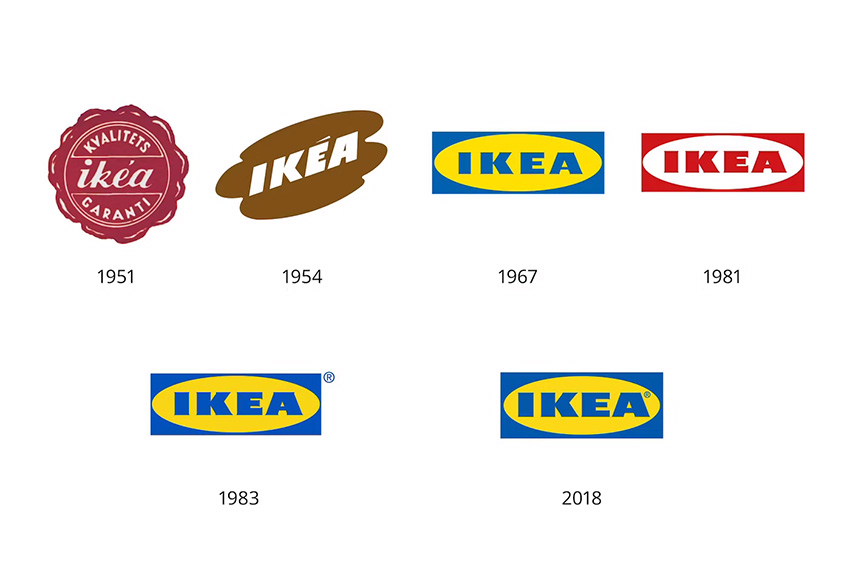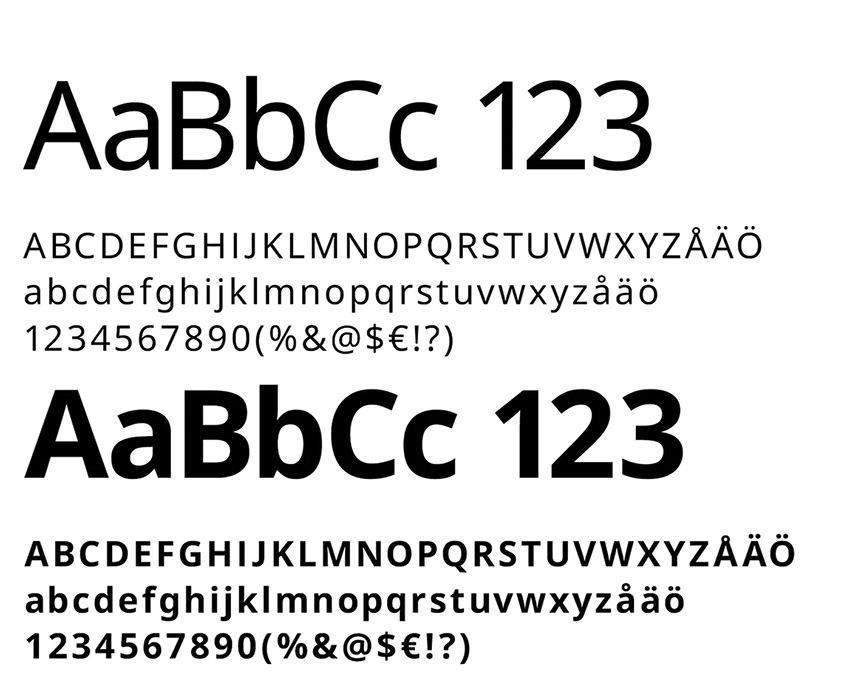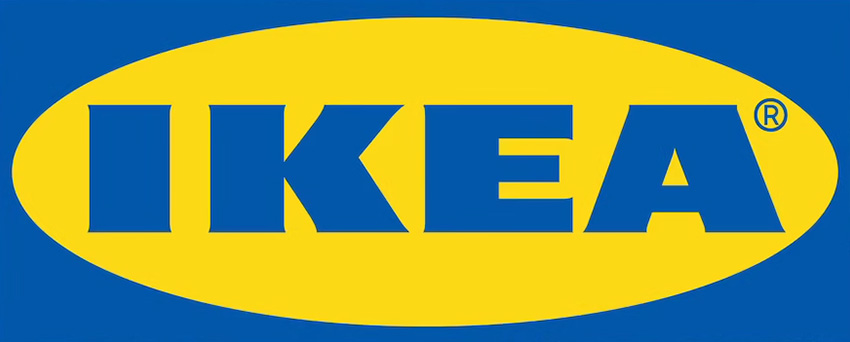
What Font Does IKEA Use?
IKEA ist weltweit bekannt für seine gut gestalteten, kostengünstigen Möbel und Haushaltswaren, und das blaue und gelbe IKEA-Logo ist ebenfalls zu einem Symbol geworden. Erfahren Sie alles über die IKEA-Logo-Geschichte, Farben, Schriftart und mehr.
IKEA-Logo. Quelle: IKEA-Website
Welche Schriftart verwendet IKEA?
Lassen Sie uns damit beginnen, die Frage zu beantworten: „Welche Schriftart verwendet IKEA?“
Die Schriftart des IKEA-Logos basiert auf einer benutzerdefinierten Schriftart namens IKEA Sans, die von Robin Nicholas entworfen wurde.
Laut der IKEA-Website basiert die Schriftart des IKEA-Logos auf einer Extrabold-Version der Futura-Schriftart, bei der kleine Serifen zu den Buchstaben hinzugefügt wurden, um die Klarheit und Lesbarkeit zu verbessern.
IKEA Sans-Schriftart
Die IKEA Sans-Schriftart. Quelle: IKEA-Website
IKEA-Logo-Geschichte
Wussten Sie, dass das Original-IKEA-Logo von 1951 rot war, weil der Gründer, Ingvar Kamprad, dachte, dass die Farbe niedrige Preise symbolisierte?
Noch mehr IKEA-Kuriositäten für Sie: Der Name basiert auf den Initialen des Gründers, gefolgt von den Initialen des Bauernhofs und der Gemeinde, in der er aufgewachsen ist. Und auf Schwedisch wird es „ee-kay-uh“ ausgesprochen, nicht „eye-kee-uh“.
Abgesehen von einem Flirt mit Braun im Jahr 1954 und einer kurzzeitigen Rückkehr zu Rot im Jahr 1981 ist das IKEA-Logo seit Jahrzehnten recht ähnlich geblieben, wobei das vertraute Blau-Gelb-Farbschema seine schwedischen Ursprünge repräsentiert. Es gab jedoch einige kleinere Anpassungen—hier ist eine grafische Darstellung der IKEA-Logo-Geschichte.
IKEA-Logo-Geschichte
IKEA-Logo-Geschichte. Quelle: IKEA-Website
IKEA-Logo-Farben
Wir kennen alle die grundlegenden IKEA-Logo-Farben: Blau und Gelb. Aber was ist, wenn Sie diese Farben genauer abstimmen möchten? Hier sind die genauen Farbcodes, laut der Brand Color Code-Website:
Es ist erwähnenswert, dass IKEA kürzlich eine weiße Version seines Logos eingeführt hat, die auf Bildern oder Videos für die Verwendung online platziert werden kann. Das ikonische Blau und Gelb wird jedoch nach wie vor für das allgemeine Branding verwendet.